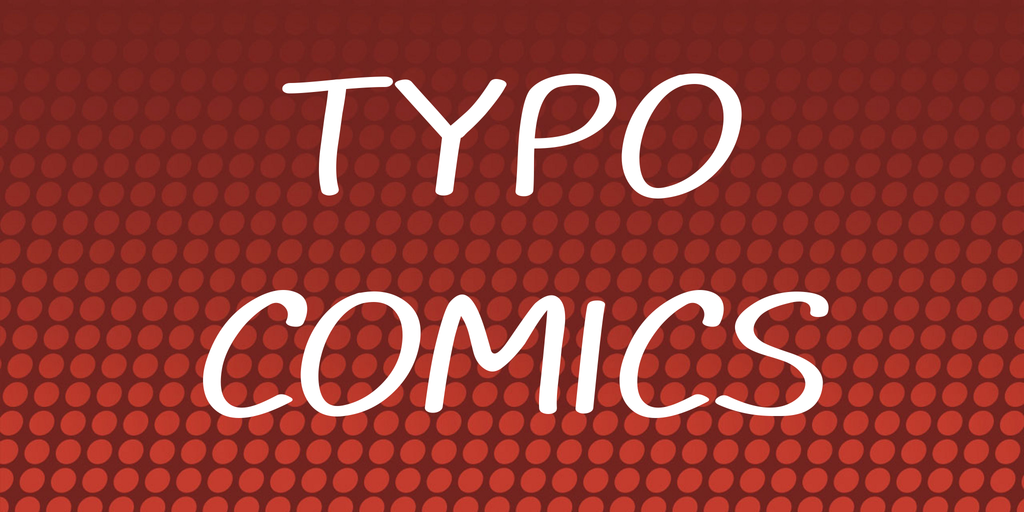
TYPO COMICS Font Family – Download Grátis
A Typo Comics Font Family é uma elegante escolha para designers que buscam um tipo sans serif moderno e versátil. Essa família de fontes foi projetada por Hamilton, oferecendo uma variedade de opções desde linhas levemente curvas até formas mais clean e minimalistas. A Typo Comics é ideal tanto para aplicativos digitais quanto para impressão em papel, proporcionando um visual sólido e confiável que combina perfeitamente com seus projetos. Se você está interessado em explorar ainda mais as possibilidades desta fonte ou precisa usar-a para um projeto comercial, visite o website do StudioTypo para obter versões completas. A Typo Comics é uma opção de primeira escolha para designers que valorizam estética e funcionalidade no mesmo grau.